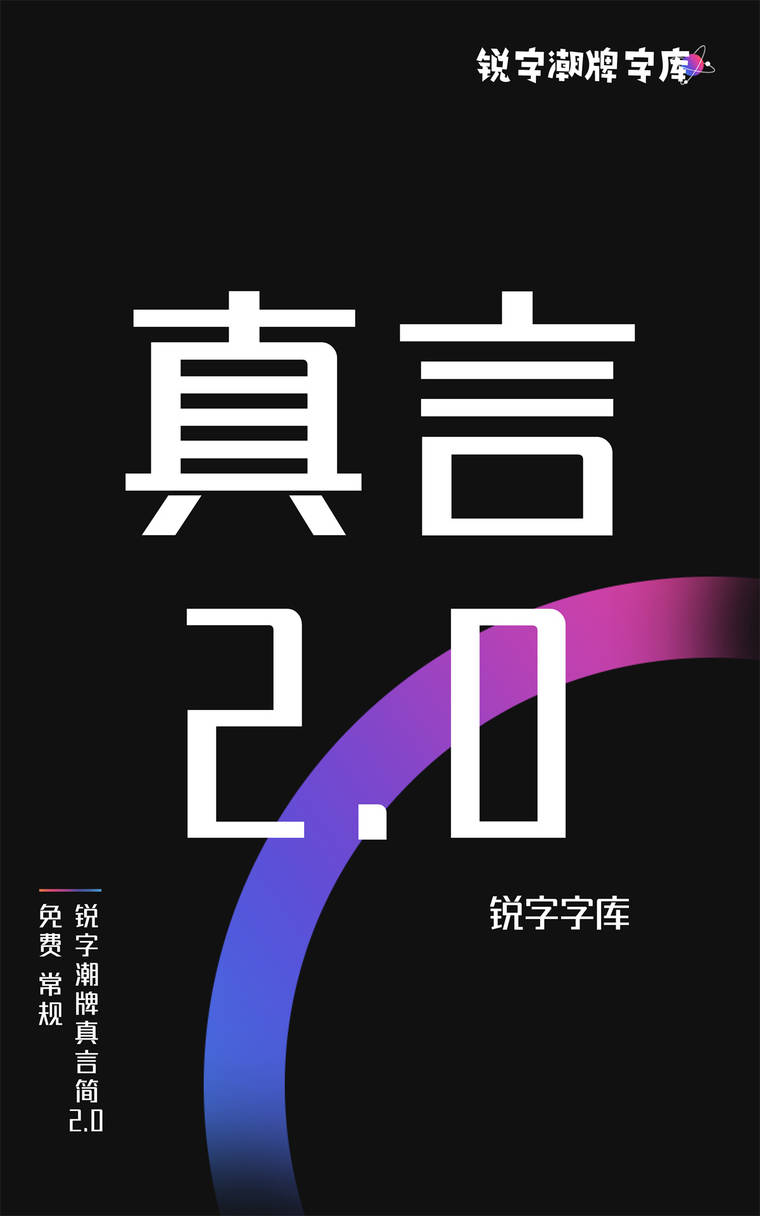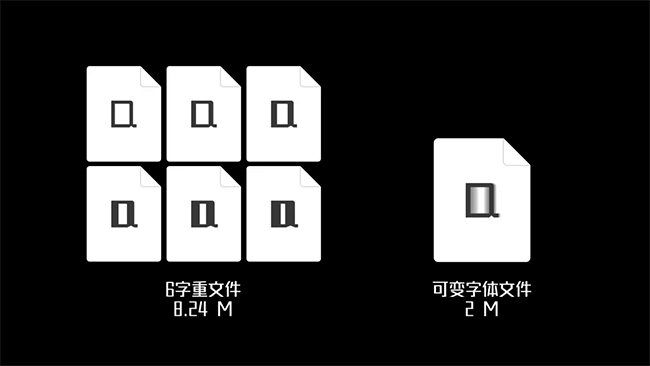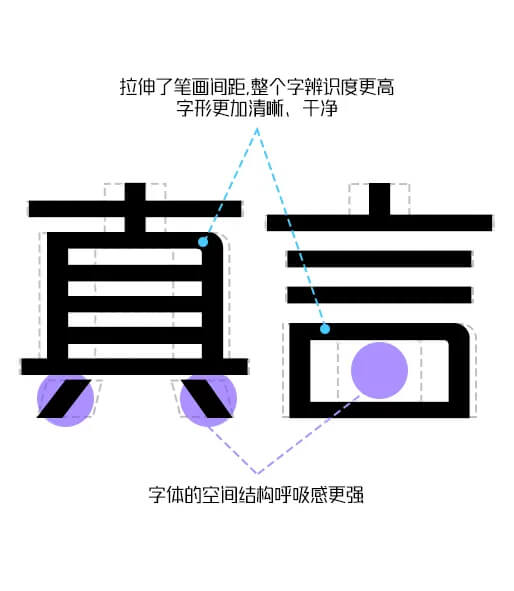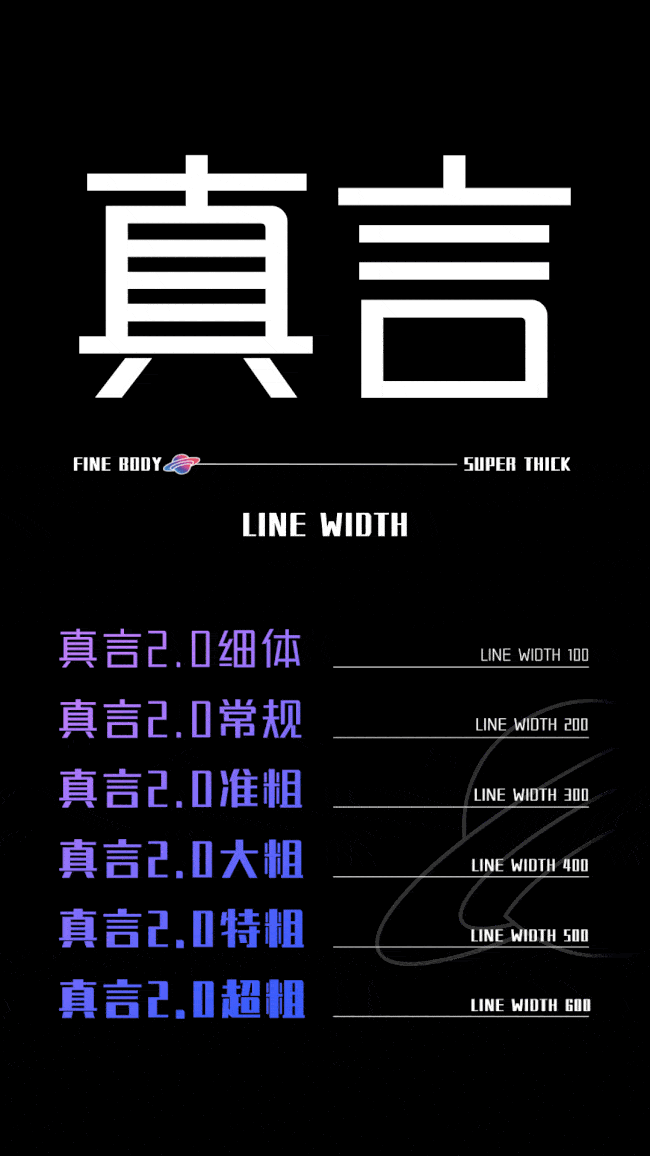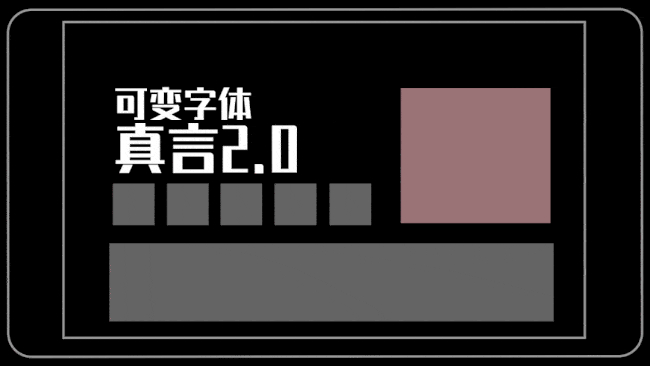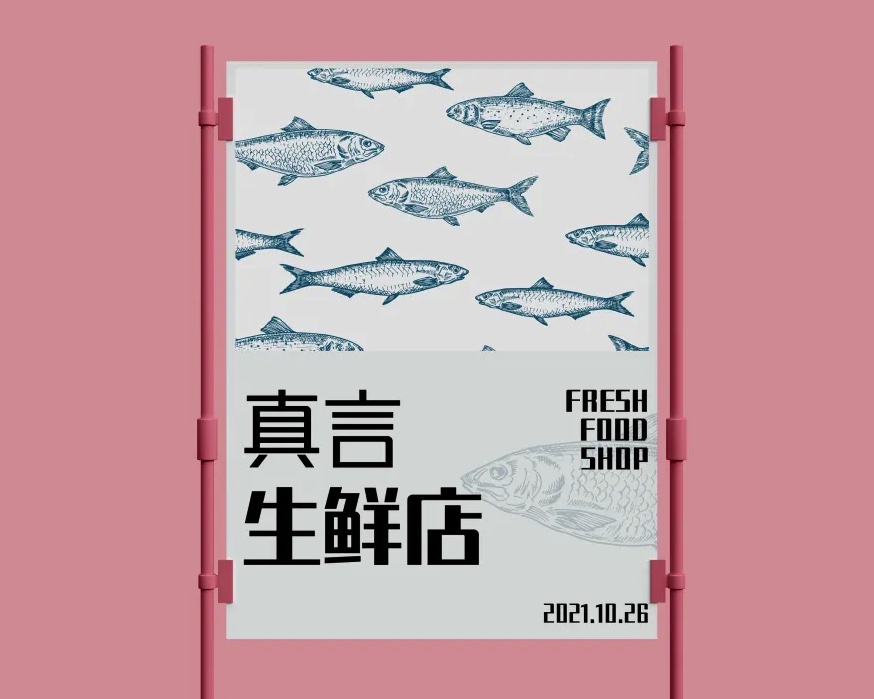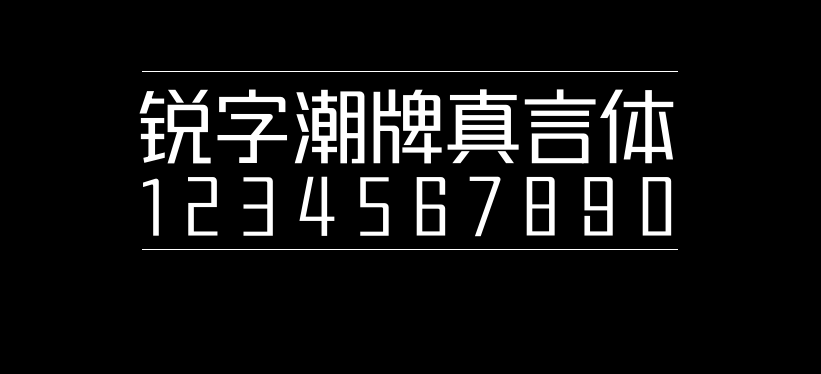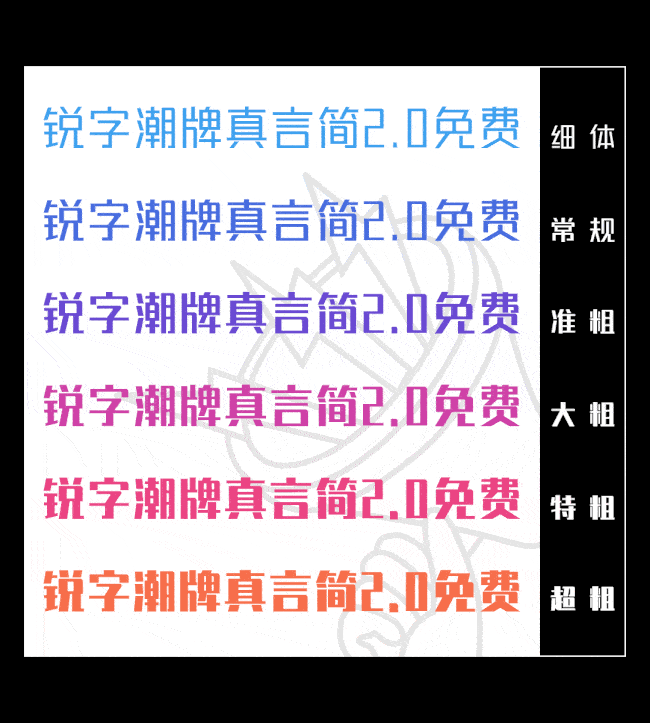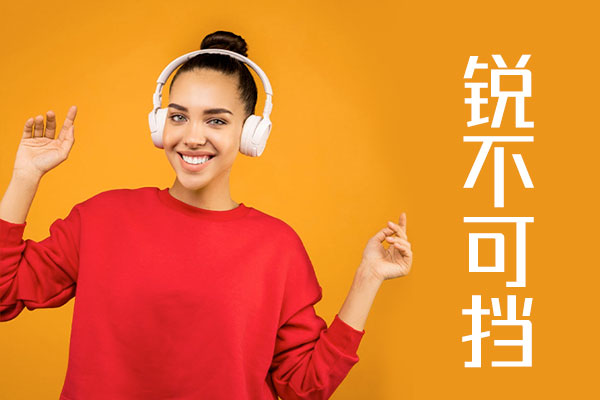
锐字潮牌真言体2.0
锐字潮牌真言体2.0(REEJI-ZhenyanGB2.0)是国内锐字库成立7周年推出的升级版字体,其前身为锐字真言体。
本次升级调整字体结构;新增6个字重;增加17个繁体与生僻的常用字,共7672个字符。并支持可变字体!可随心所欲自由变换,把字体玩出花!现面向社会开放下载,下载网址:www.reeji.com
1、更具呼吸感通用性更强
锐字潮牌真言简2.0细体文字,结构干净,笔画移除了粗细对比,因此辨识度更高,字形看起来更加清晰、干净。中性的笔画设计与分隔使得细体文字通用性更强,排版也更有质感,画面看上去更加轻盈,具有呼吸感,更容易阅读。
2、系列化字体更加潮流、高级
升级后的系列化字体,在保持横画不变的基础上,将竖画粗细进行变化,随着字重的减小,横画与竖画粗细对比减弱,增添了字的留白与内部空间感,给人潮流、高级之感。
3、6字重全方位免费传播品牌真声音
品牌声音也有跨度,从低声吟唱到放声高歌,你的品牌要跨越几个度?
锐字潮牌真言简2.0在1.0版本基础上,衍生出5款系列化字体,共细体、常规、准粗、大粗、特粗、超粗6款字重,全面传播品牌真声音。
4、潮牌可变字体拥抱变化新世界
本次字体升级的另一个惊喜:新增可变字体技术!将含有字体粗细变化的字体文件,包含在单个字体文件中,从而实现随意切换,让字体呈现出不同的形态。
字体自由变换,具有无限延伸的可能性
安装可变字体文件后,可以通过滑动调节字体的粗细,在这种自由的形态下,设计师可以按照设计需求、喜好来控制字体的使用范围,让字体具有无限延伸的可能性。
更灵活的使用场景,全新的视觉体验
可变字体的应用,突破了传统字体的限制,比如网页适配,不同的显示器设备屏幕比例适配等,让字体在不同的传播媒介中可以更灵活地运用。
除此之外,可变字体还拥有更多的创意空间与可能性,为品牌带来全新的视觉体验。
体积更小,更节省存储空间
一般传统字库里6个字重,分别以独立的形式存储,所占空间大概是8.24MB,而一款支持可变字体的文件仅需2M,减少了字体文件的大小,存储空间大大提升。
我们期待更多设计师和品牌,以更灵活、美观的视觉表达,开启未来潮牌可变字体新纪元,透过字体更好地传播品牌声音!